2019 年最适合设计师的免费字体
CASA 模具
Casa Stencil 是一种美丽、优雅的模板字体,具有柔和的曲线和侵蚀感。 它的存在一定会让您的设计与众不同。 它是为您所有的标题和徽标需求而设计的。
卢梭装饰
Rousseau Deco 是由 Mariabno Diez 设计的装饰艺术风格字体
罗莎丽娜
Rosarina 是由阿根廷罗萨里奥 Antenah Studio 的 Mariano Diez 设计的大写浅色字体。 它既简单又优雅,可以作为标题出现,用于书籍/杂志封面设计、广告和传单。
垫片
这是一个实验性的未来字体项目,由 Antenah 的 Mariano Diez 设计。
时空衬线
Chronos Serif 是一款优雅的展示衬线,具有三种变体。 充满细节和精致的曲线,它肯定会提升您的高端项目。
生锈
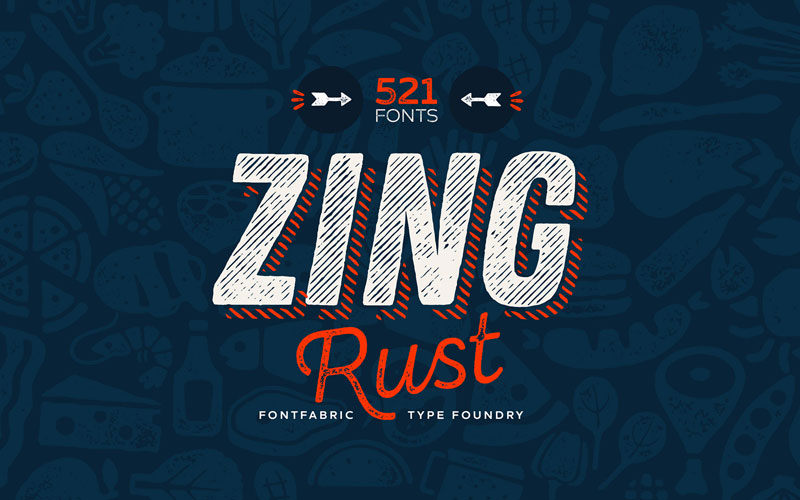
Zing Rust™ 是一个非常庞大的包,包含出色的手工制作的 521 字体! 顾名思义,Zing Rust 代表您的想法和大胆设计的重要新鲜感。 各种精心制作的风格让您有机会将大量无衬线、脚本、图标和丝带与阴影、铁锈、半色调点、线条等结合起来。 每个都有许多权重,为您提供想象力的终极工具。
Anaphora – 免费字体
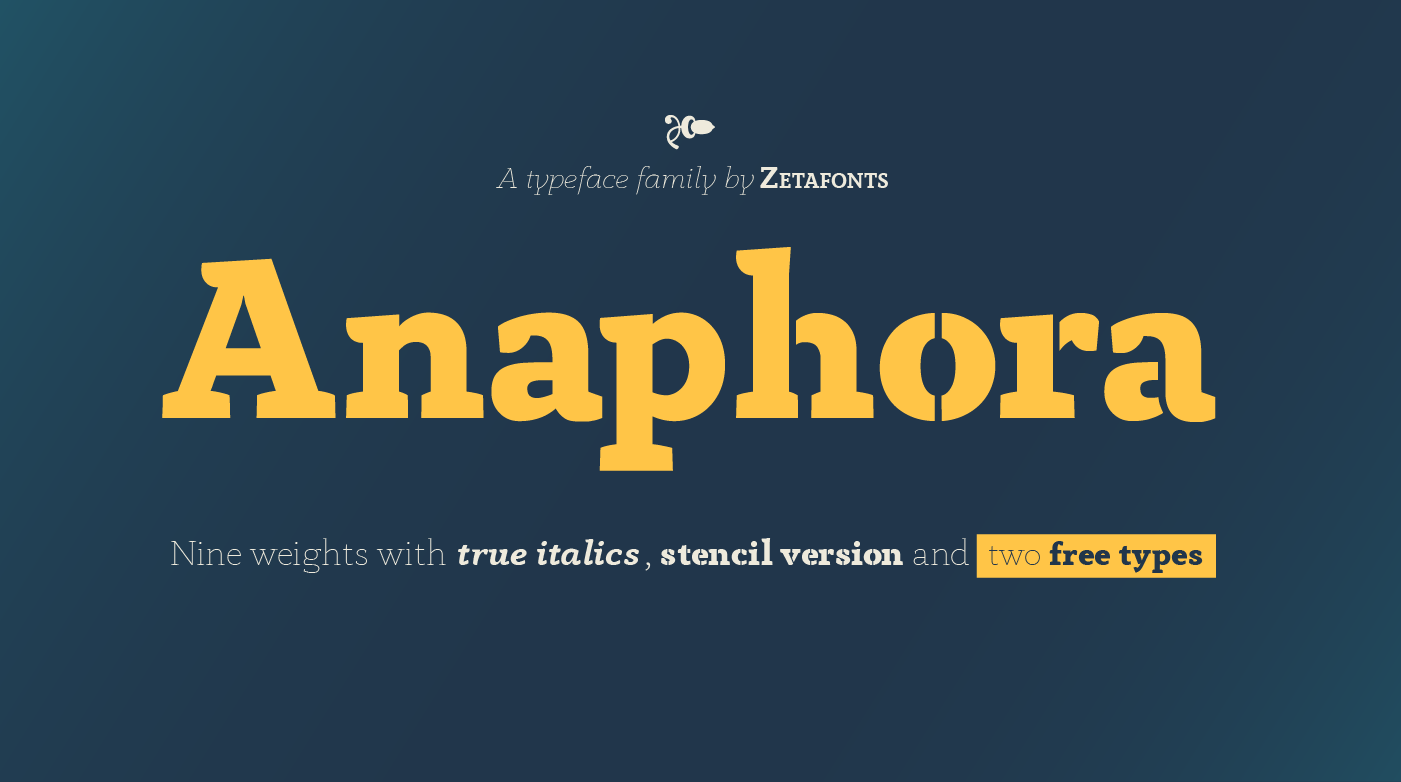
Anaphora 是由 Francesco Canovaro 与 Cosimo Lorenzo Pancini 和 Andrea Tartarelli 设计的现代衬线字体。 它采用楔形衬线设计,具有从细到重的九种粗细,每个粗细都具有真正的斜体样式,适用于各种编辑和广告用途。
Peace Sans-免费字体
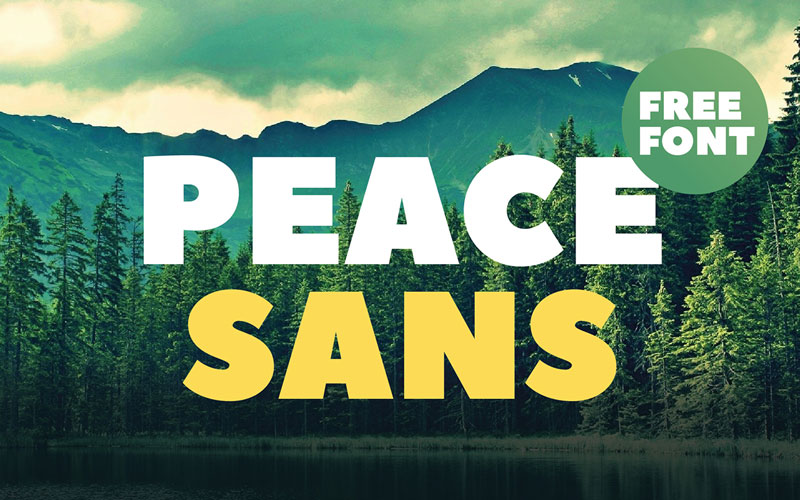
Peace Sans 是一款用爱制作的免费粗体字体! 它可以使您的排版更加和平和友善。 无论如何使用它,它是完全免费的。 它是在Type Type School的学习过程中创建的。
带有两种免费字体的黑色文本系列
Blacker具有扩展的字符集,涵盖使用拉丁字母和俄语西里尔文的 70 多种语言。 开放式特征包括小型大写字母、四组数字、分数、优劣数字、替代形式和任意连字。
MACBETH-FREE SVG 字体
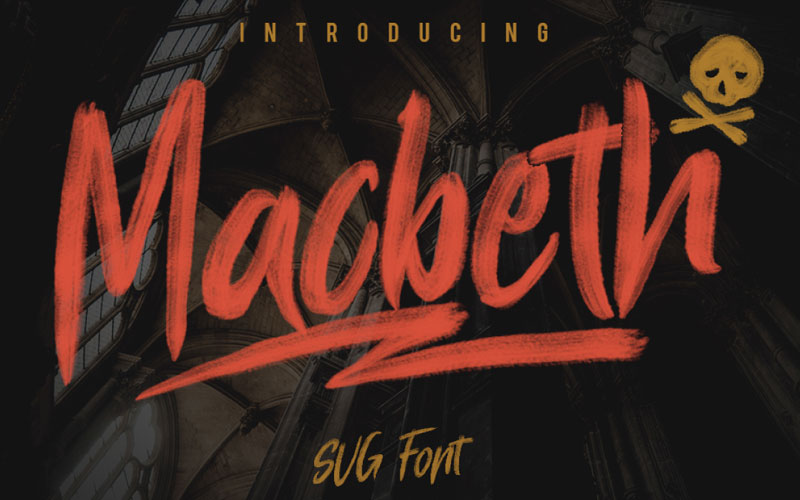
Macbeth 是 Giemons 独特的全新手绘 Open Type SVG 字体。 这种新的字体格式允许在每个字母中呈现惊人的真实细节。 这是一种带有大写和小写字符以及数字、标点符号和一些额外标记的激进字体。 将其用于出色的展示、标签、服装、海报、电影标题、专辑封面、徽标等等。
无盐摩卡笔刷字体
Salted Mocha 是由 Stephanie Arsenault 设计的手绘笔迹字体。 Salted Mocha 使用我们的免费笔刷包在 iPad Procreate 应用程序上创建,具有真实的笔触纹理。 它的循环笔触和弹跳基线给它一种有趣好玩的感觉。 非常适合突出的品牌、邀请、报价和印刷品。 免费供个人和商业使用!
ENDESTRY – 书法 | 自由现代字体
Endestry 是一款甜美、性感、有弹性和流畅的现代书法脚本字体,具有个人风格,让您的最新项目看起来很棒。
无扩展字体 | 字体系列
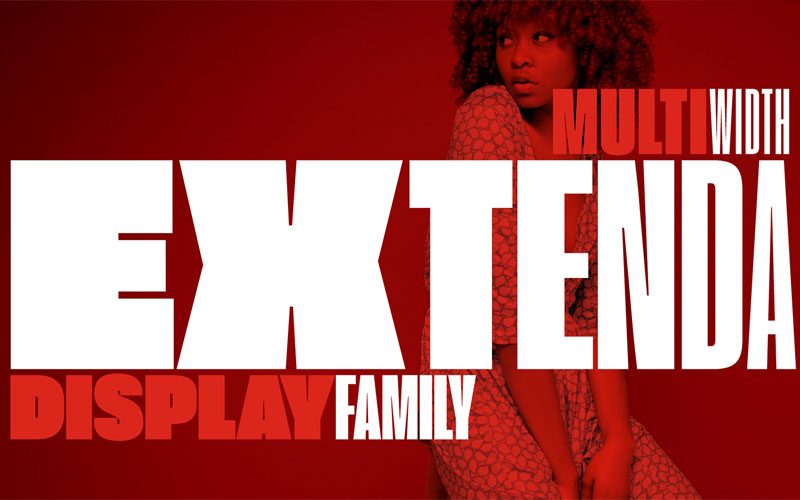
Extenda 是由 Francesco Canovaro 与 Andrea Tartarelli 和 Cosimo Lorenzo Pancini 设计的可变宽度无衬线字体系列。它的创建旨在为设计师提供强大而灵活的工具,以创建强有力的标题、徽标和显示文本,间距紧凑且空间覆盖范围最大.
无大学风格的优雅模板字体
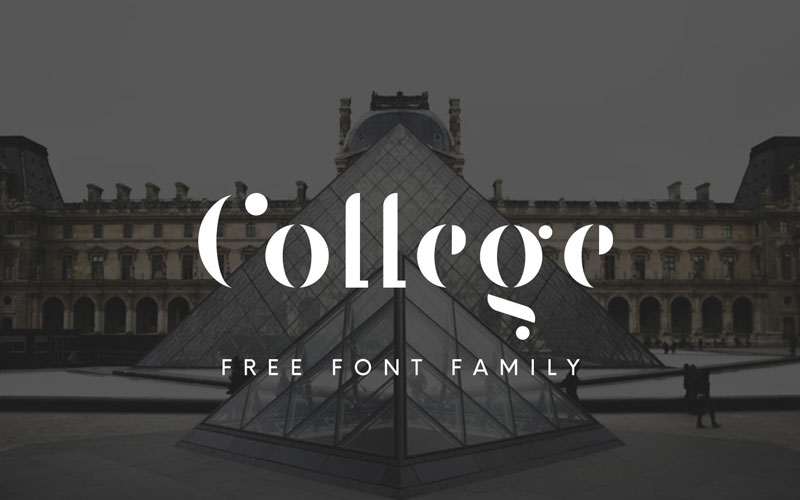
College 是来自 Corentin Riviere 的免费优雅模板字体。 它最初是一个实验项目,是为了向法兰西学院致敬,现在是一种功能齐全的经典风格字体。 它的字体受到法兰西学院建筑的拱门和柱子的启发,并帮助创造了这个项目的整体感觉。 免费供个人和商业使用。
ANURATI-Free 字体
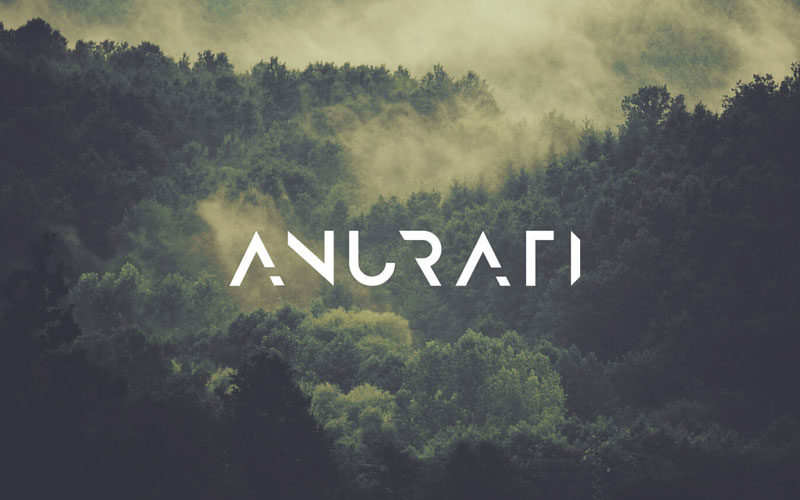
Azonix-Free 现代字体
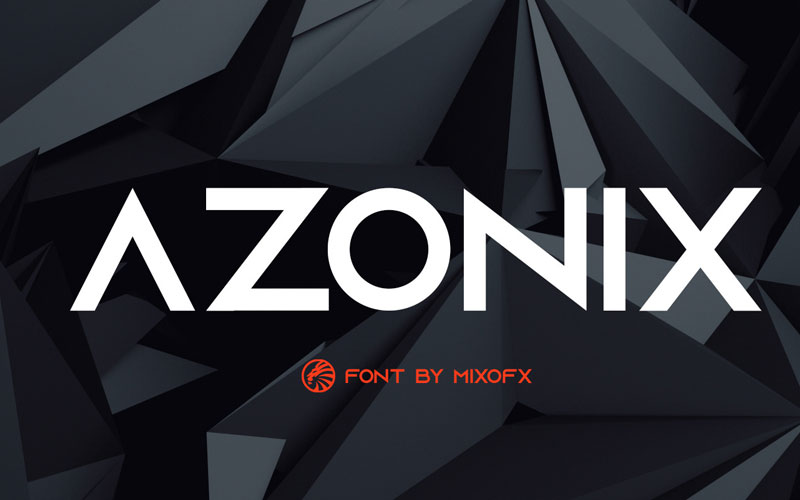
Azonix 是一种现代无衬线字体。 这种字体由粗体几何大写字母、数字和标点符号(符号)组成。 我希望在评论中看到一些反馈。 我将来会制作更多字体,所以请随时关注我,以免您错过。
GILLIGAN SHUTTER-FREE脚本字体
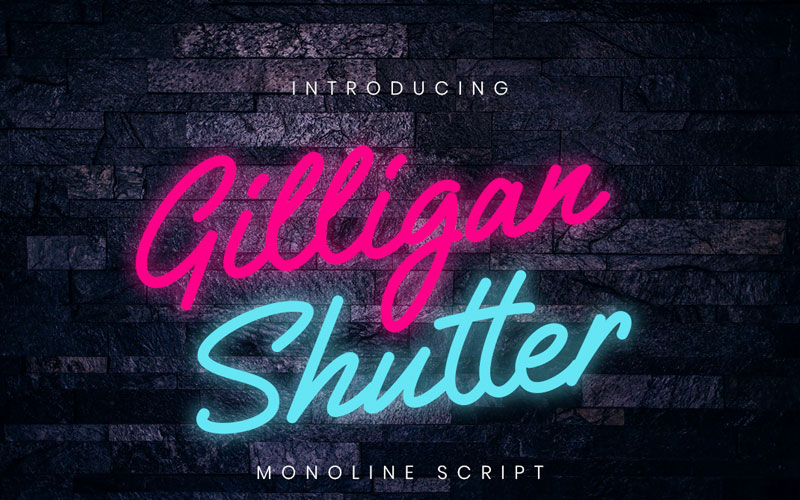
Gilligan Shutter Monoline 是一款精致的标志性单线粗体系列,可为您的最新项目提供自然的字体。
Metrica-免费字体下载
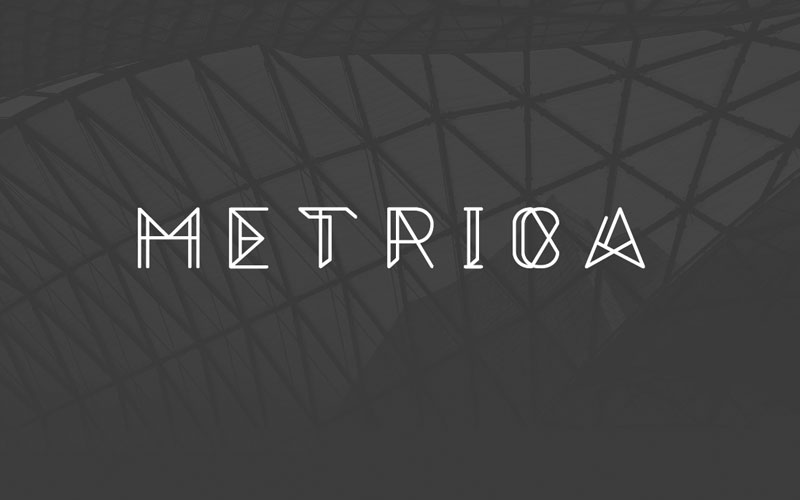
Metrica 字体是一种新的大写、锐利和机械的字体。 Metrica 字体采用平面几何设计——免费供个人使用(可根据要求提供商业用途)。 利用来自建筑设计的敏锐观点的影响,我想要一些非常引人注目且立即可识别的东西。
BERG-FREE 分层字体系列
Berg 是来自 Brosnes 的一个巨大的分层字体家族。 受复古标志画、海报和标签的启发,Berg 具有非常引人注目的强大形状。 您可以将此 berg 系列字体组合成许多不同的样式分层。 适合:您可以将此字体用于各种目的。 例如品牌、徽标、标志、海报、标签、信头、凸版、包装设计、印刷设计、服装、书籍封面等等。
Osgard-Pro-字体
Osgard Pro 是一款功能强大、奢华的字体,采用了罗马式字体的流畅曲线元素,并将它们与 Blackletter 的哥特式风格相结合。 可作为 webfont/web 字体使用。 免费字体。 免费模板字体。 标志。 标识。 图标。
KENJO-字体 | 样式表
2 字体系列 | 6 Fonts Kenjo I & II 是一个显示字体集合,具有日本/装饰艺术风格的影响。 完全大写(当前),它包含标准的更通用的 Serif(Kenjo I),以及更时尚的风格化选项(Kenjo II)。